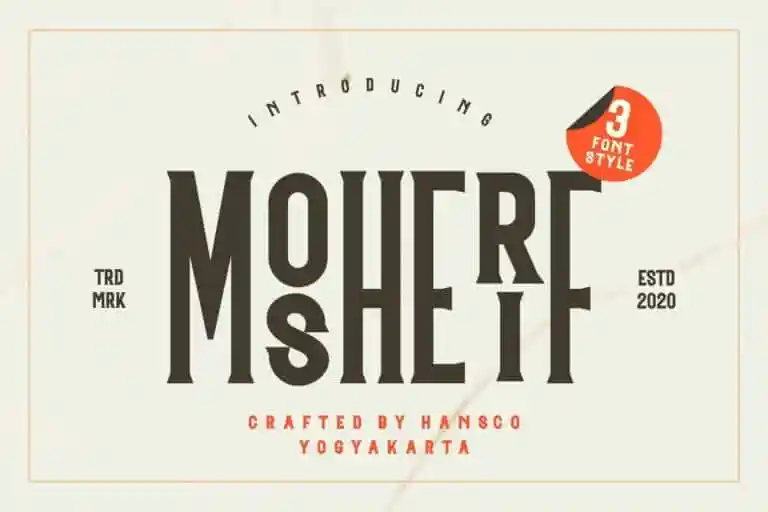
A Mosherif Display Font é uma fonte sans-serif que traz um toque único através de suas ligaturas únicas, garantindo um design moderno e limpo. Foi criada pelo designer HansCo para quem busca imprimir sua marca com alegria e sofisticação. Este tipo de letra impressiona em áreas como criação de logotipos e design editorial por seu aspecto e sensação, resultando em projetos mais agradáveis e fluídos. A inclusão especial de ligaturas especiais na Mosherif Display Font torna ainda mais distintivo seu uso, elevando o nível do design para um patamar moderno e chamativo. Este tipo de fonte é perfeita para quem deseja dar ao seu design uma aparência vibrante e atual.